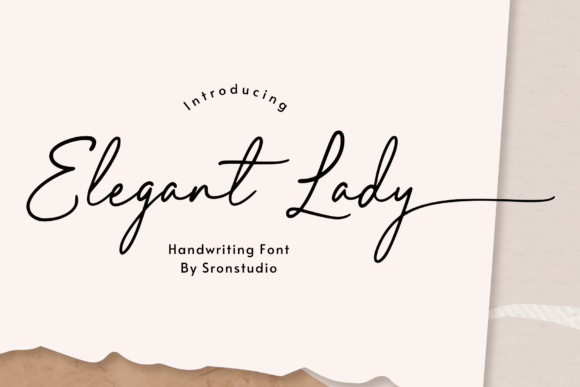
Elegant Lady
適切なデザイン要素を見つけるのは難しい場合がありますが、Elegant Ladyは作品を即座に引き立てる優れたコレクションを提供します。
POD(オンデマンド印刷)製品、結婚式の招待状、またはソーシャルメディアのグラフィックを作成している場合でも、Elegant Ladyは理想的です。